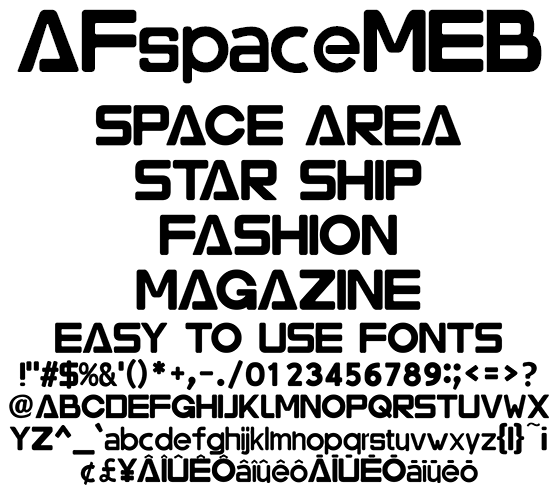
大見出し専用欧文フォント AFspaceMEB
AFspaceMEB
「AFspaceEB」の角に丸みをもたせ大見出し用に特化しました。未来感あるキャッチな場面でご利用ください。同人系、コミック、アニメ、ゲームに最適。パンフレット、リーフレット、フライヤー、ファッション系コンテンツに使えるフォントです。